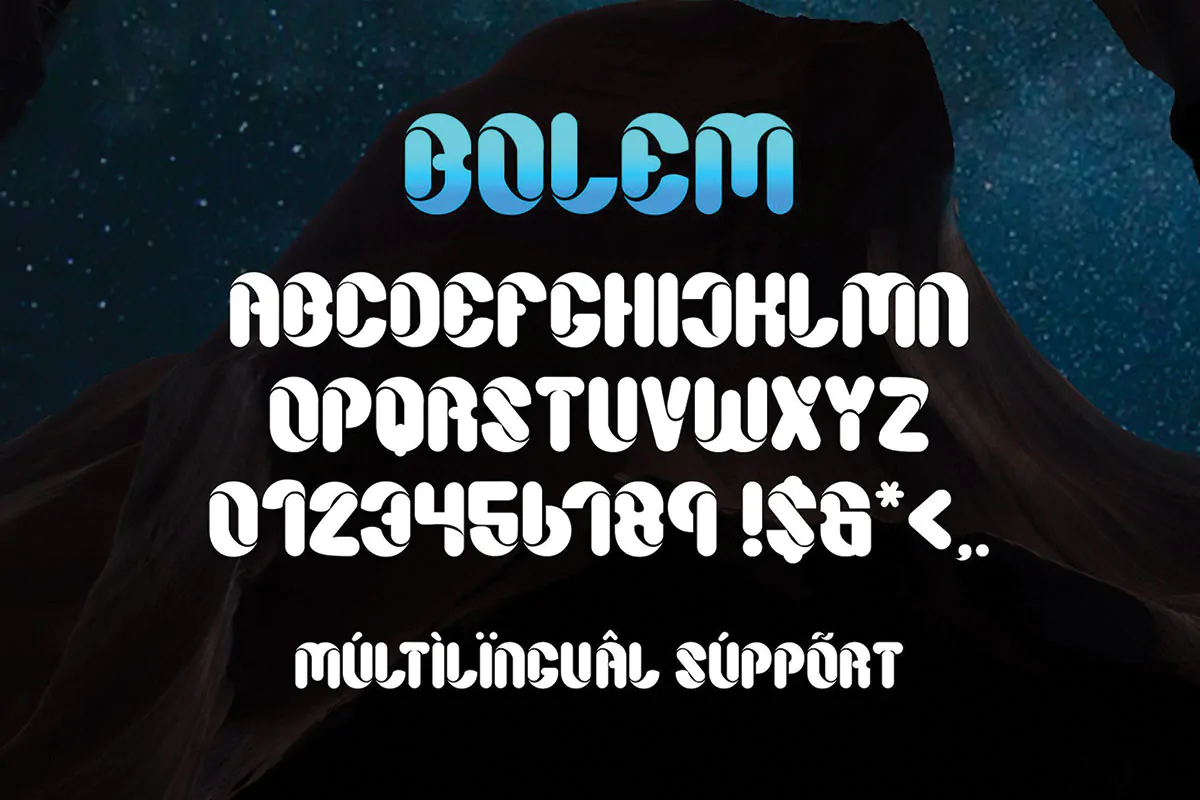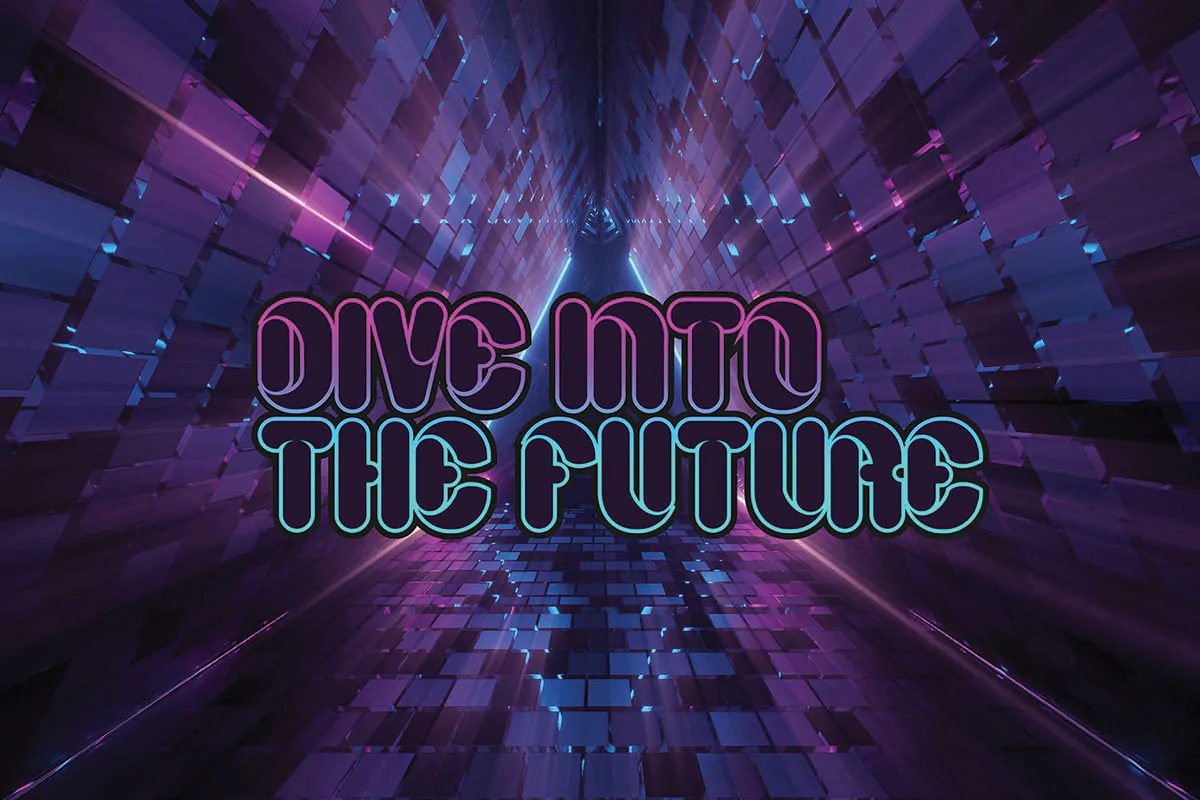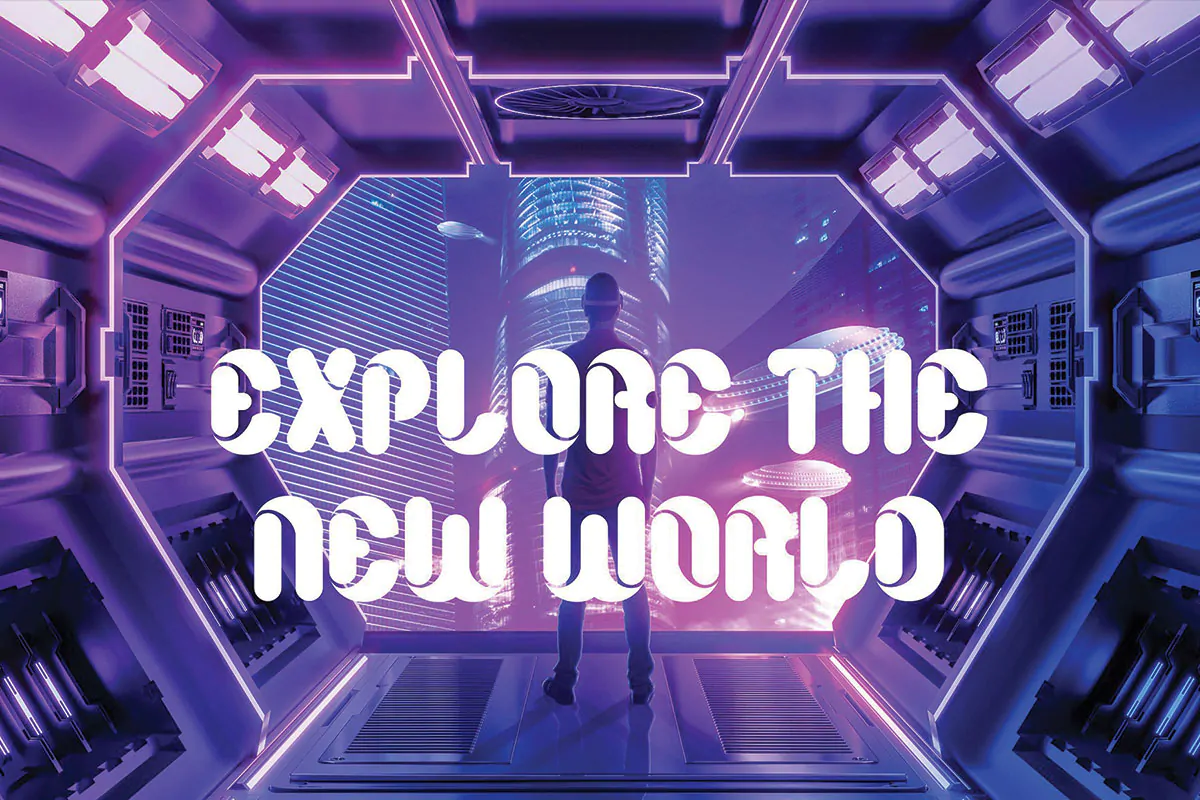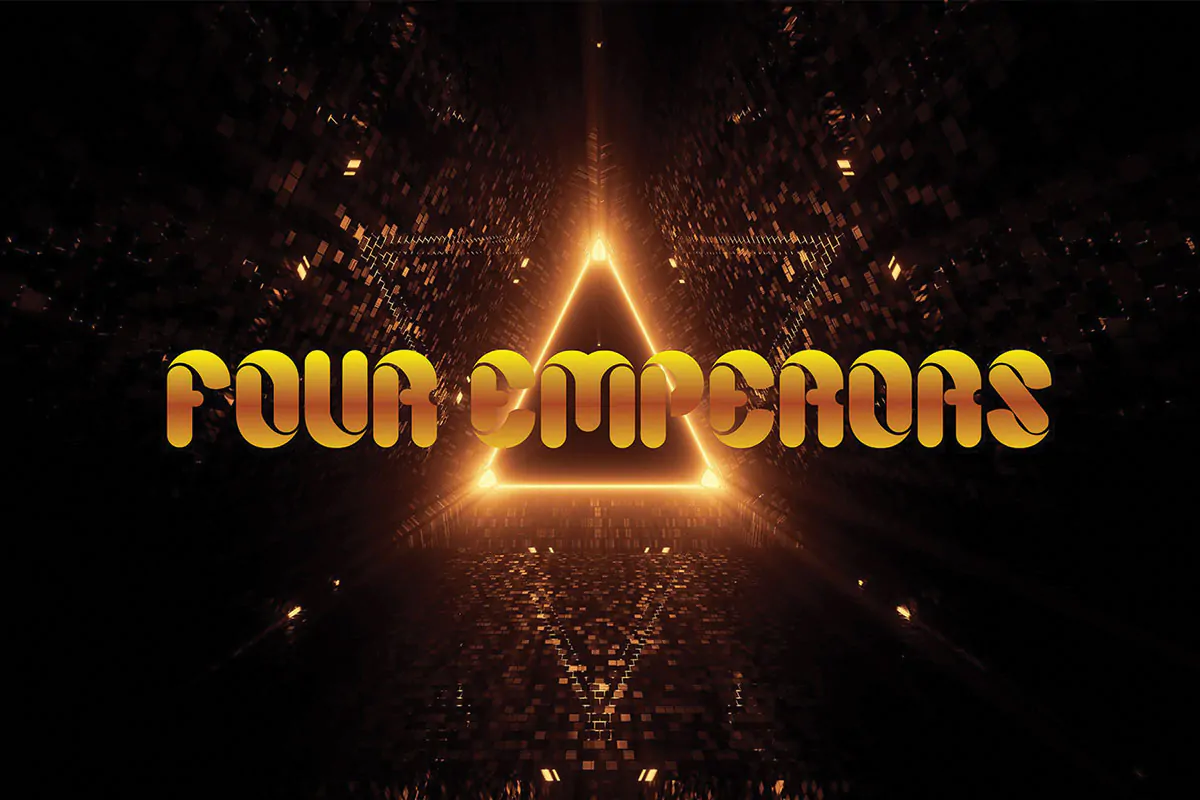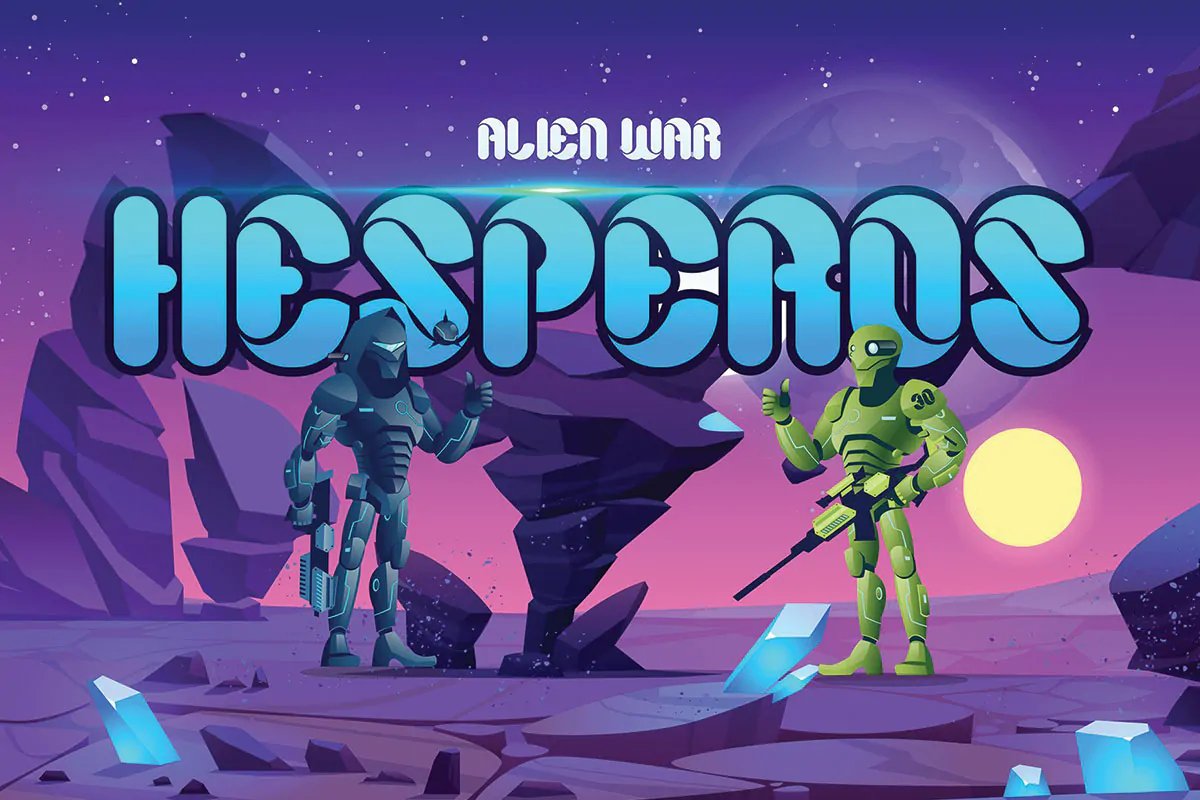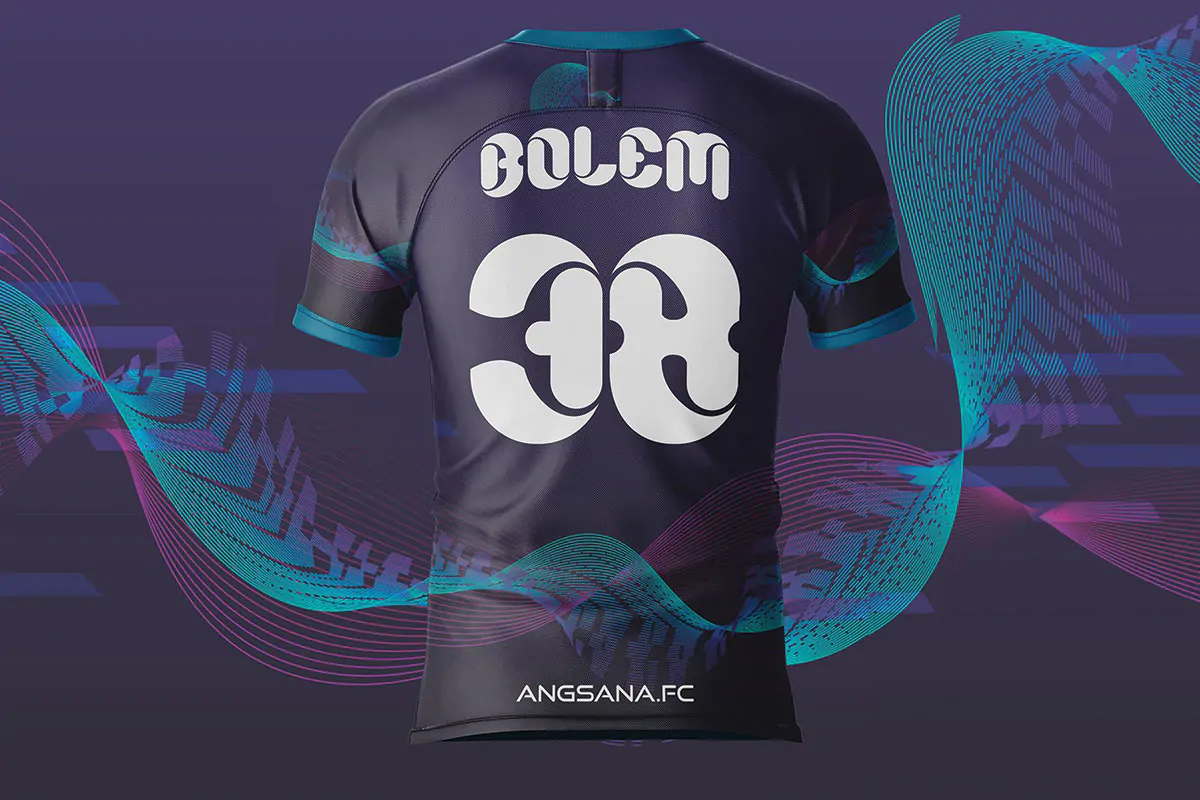
فونت تخیلی و آینده نگر Bolem
فونت تخیلی و آینده نگر انگلیسی
فونت تخیلی و آینده نگر Bolem یک قلم نمایشی فوق العاده زیبا است که از آن میتوانید در طراحی انواع لوگو، پوستر، کاور آلبوم موسیقی، بنر، بسته بندی محصولات، ظروف یکبار مصرف، لوازم التحریر، چاپ تیشرت و … استفاده کنید.